CSS 字体新玩法之彩色字体
CSS Fonts Module Level 4 工作草案中的一大新特性即为 Color Font 的支持,来了解一下吧!
为什么要使用彩色字体
如果你们设计师想在某些特别的专题活动中使用下图的字体作为标题字体进行展现,怎么办呢?做成图片咯。然后你可能会遇到这几个问题:不同屏幕下的适配,要是只做一种尺寸的图,放大或缩小后的效果都不太好。直接做成 SVG?好像不能复制到 Word 里面加粗啊,也就是说,这种做法使得这些“文字”本身失去了真实文字该有的能力。
此时彩色字体的好处就显现出来了。既能达到视觉效果上的要求,还拥有常规文字的功能,能够复制,能够粘贴,还可以被屏幕阅读器阅读,丝毫不妨碍常规操作。
Playbox by @Matt Lyon
什么是彩色字体(Color Font)
初识彩色字体
在我们所熟知的传统字体中,字体文件本身仅仅描述了字体的外形特征,这些特征一般包含着矢量的轮廓数据或是单色调位图数据。在浏览器渲染单色字体时,渲染引擎使用设定的字体颜色填充字形区域,最后绘制出对应文字及其设定的颜色。而彩色字体中,不仅仅存储了字体的外形特征,还保存了颜色信息,甚至还能在字体中提供不同的配色,增加了灵活性的同时也更具丰富的外形细节。
日常使用中最常见的彩色字体要数 Emoji 表情了。例如在 Windows 10 上,Segoe UI Emoji 就属于一款彩色字体。
通常彩色字体还会包含一些兼容信息,这些兼容信息包含 Unicode 编码的单色字形数据,使得在一些不支持彩色字体的平台上,仍然能够像渲染普通字体一样将彩色字体的字形渲染出来,达到一种向后兼容的效果。
彩色字体的实现标准
在彩色字体设计的发展历史上,由于各家有自己的实现方案,导致在 OpenType 字体中嵌入的色彩信息标准也不尽相同。在最新的 OpenType 标准中,就有多达四种彩色字体数据的描述格式。
- SVG,由 Adobe 和 Mozilla 主导的矢量字体标准。其中不仅包含了标准的 TrueType 或 CFF 字形信息,还包含了可选的 SVG 数据,允许为字体定义颜色、渐变甚至是动画效果。SVG 标准中的配色信息也将存储在 CPAL 中。
- COLR + CPAL,由微软主导的矢量字体标准。其中包含 COLR 即字形图层数据和 CPAL 配色信息表,对其的支持集成在 Windows 8.1 及之后的版本中。
- CBDT + CBLC,由 Google 主导的位图字体标准。其中包含了 CBDT 彩色外形位图数据和 CBLC 位图定位数据,对其的支持集成在 Android 中。
- SBIX,由 Apple 主导的位图字体标准。SBIX 即标准位图图像表其中包含了 PNG、JPEG 或 TIFF 的图片信息,对其的支持集成在 macOS 和 iOS 中。
浏览器对各种标准的支持
看到这么多种标准,参差不齐的浏览器支持,你可能会想难道又要根据UA派发不同格式字体做兼容么?告辞!
少侠且慢!
在 2016 年的时候,各大厂商最终同意使用 OpenType SVG 作为彩色字体的标准,也就是上面提到的 SVG,也是 W3C 目前所用的标准。相信在不久各大厂家浏览器将逐步支持 W3C 所用的 SVG 标准。
字体模块标准的现状
CSS Fonts Module Level 3 :目前处于候选推荐状态,是主流浏览器都已大部分实现的标准,最新一版候选标准发表于今年的 6 月 26 日。Level 3 标准基于之前的 CSS3 Fonts 以及 CSS3 Web Fonts,并将字体加载事件相关的标准移入 CSS Font Loading模块中。
CSS Fonts Module Level 4:Level 3 的下一代标准,目前处于工作组草案状态,最近一次草案更新于 4 月 10日。该版本草案基于 Level 3,新增的属性中比较新颖的功能,也就是本文将要介绍彩色字体(Color Font)的支持。
CSS 彩色字体相关标准
在支持彩色字体的浏览器中,虽然能够正确渲染,但是你却无法控制使用字体中内置的其他配色。那么在 Level 4 标准中,就新增了一些彩色字体相关的标准让我们能够更好地使用。接下来我们就来看看吧。
选择字体配色:font-palette
前面我们了解到,彩色字体通过 CPAL 表是可以拥有多种不同的配色方案的。font-palette 有三个内置的参数以及支持自定义配色来达到修改配色方案的效果。
normal:浏览器尽可能地将该字体当作非彩色字体进行渲染,并选择一个最适合阅读的配色方案。浏览器在做决策时还可能将当前设定的字体颜色color加入决策条件中。还有可能自动生成一组未内置在字体中的配色方案进行渲染。light:一些彩色字体在其元数据中标明某个配色方案适用于亮色(接近于白色)背景中。使用此数值,浏览器将会直接使用标记了该特性的首个配色方案进行渲染。如果字体文件格式无元数据或时元数据中未标记相应的配色方案,那么此时该数值的行为与normal相同。dark:正好与light相反。- 自定义:上面我们介绍了三种基本的配色选择,那么如果要使用其他的配色方案或是要自定义,我们将要借助接下来介绍的
@font-palette-values的帮助。
示例:
h1 {
font-family: Segoe UI Emojil
font-palette: light
}
自定义字体配色:@font-palette-values
@font-palette-values用于定义指定字体的配色规则。它允许开发者不仅可以自由选择字体内置的各种配色方案,还能自定义配色方案。而font-palette选择自定义配色方案也是通过本规则设置。
它的基本定义规则是@font-palette-values name,name 即为本配色规则的自定义规则名称。
下面通过其中的三个关键属性进行解释。
font-family
首先,在为字体设置配色时,我们先要指定这些配色信息是设定在哪个字体上的。通过font-family即可将当前配色配置绑定到某个字体上。
@font-palette-values Snow {
font-family: TriColor;
}
base-palette
在作者制作彩色字体时,往往内置了很多种字体配色,存储这些信息时,每个不同的配色方案有自己对应的 id,或者叫做 index。使用 base-palette 进行选择。
@font-palette-values Snow {
font-family: TriColor;
base-palette: 5;
}
color-x
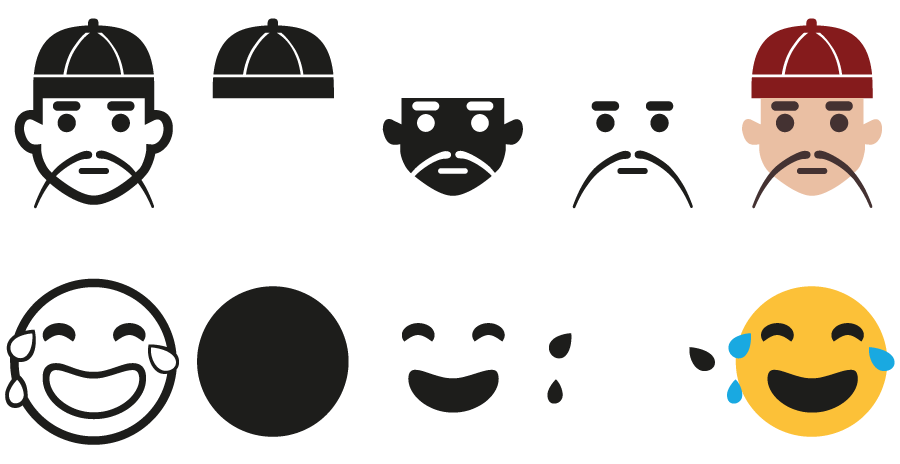
上图展示了 COLR 对字形的分层。 COLR 将字形的多个部分分为多个图层,并按照特定的顺序将图层合并成为一个完整的字体。每一个图层都由 CPAL 中的配色信息进行上色。为了达到更强大的自定义效果,标准中使用 color-x 属性提供对特定图层颜色进行复写的能力。其中的 x 即为图层 id。
@font-palette-values RedSnow {
font-family: TriColor;
base-palette: 5;
color-1: rgb(255, 0, 0);
}
上述例子展示了如何通过 color-x 对图层颜色进行复写。通过 base-palette: 5 选取自带的配色,并通过 color-1: rgb(255, 0, 0) 将该配色中 id 为1的图层颜色修改为红色。
Level 4 其他值得注意的新属性
font-min-size, font-max-size
与属性名称描述的一样,这两个属性将限制font-size最终的数值。如果font-size的计算值超出设定的最大和最小值,font-size的最终数值将会被直接修改为 font-min-size或font-max-size。 这对于响应式设计来说是比较有用的,将字体大小限制在一个范围,使得字体不会变的过大或过小。
总结
Fonts Module Level 4 中有趣的新功能还是挺多的,具体效果和标准改进得等各大浏览器开始慢慢支持才能知道,让我们拭目以待吧。